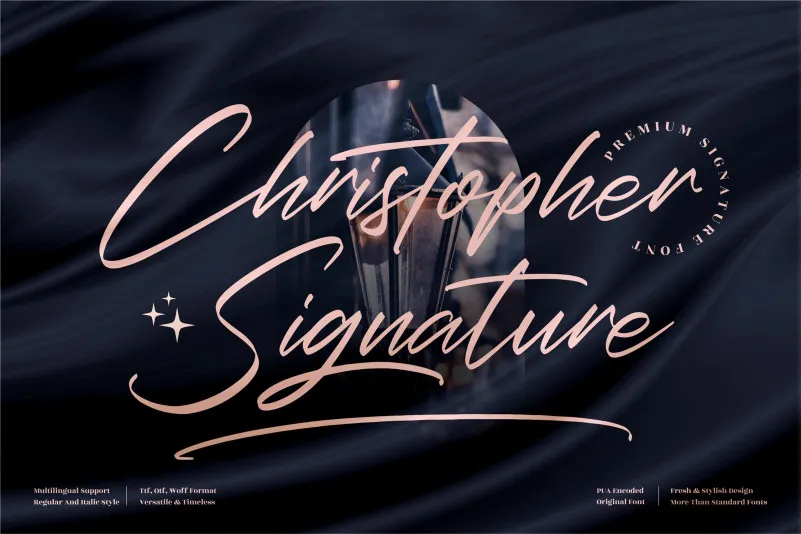
Christopher Signature Font – Download Grátis
Esta é uma fonte de estilo script premium adequada para uma ampla variedade de projetos, desde logomarcas até cartões de convite, passando por embalagens de produtos e materiais decorativos. Seja este um design para seu próprio estúdio ou até mesmo a próxima coleção de roupas que você está criando, ela tem o toque sofisticado que complementa seus esforços. Ideal para criações delicadas como cartões de nome, embalagens personalizadas, materiais publicitários e até mesmo suas capas de livros. A fonte Christopher Signature Font é perfeita para aqueles momentos especializados onde você quer transmitir um toque extra de sofisticação e individualidade em seus projetos. Ela se destaca como uma opção elegante e versátil, ideal tanto para os mais criativos quanto para os que valorizam a qualidade em cada projeto.